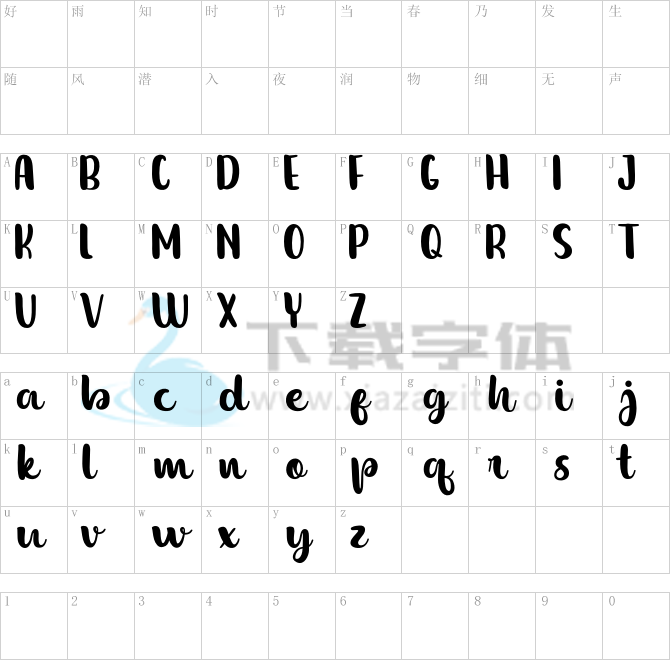
Ameliya Emma.otf字体下载,这款字体结构工整、笔画清晰,兼顾美观与易读性,适用于标题、正文、海报、包装、LOGO 等多种场景。字形优雅稳定,风格百搭耐看,适配日常排版与创意设计,让文字呈现更舒适、更具质感。Ameliya Emma.otf字体下载一笔一画,皆是细节,以均衡的比例、流畅的线条打造舒适视觉体验,字形端正大气,风格简约现代。无论是商业设计、品牌宣传还是日常排版,都能轻松驾驭,让文字更有格调与力量。Ameliya Emma.otf字体下载字体下载。